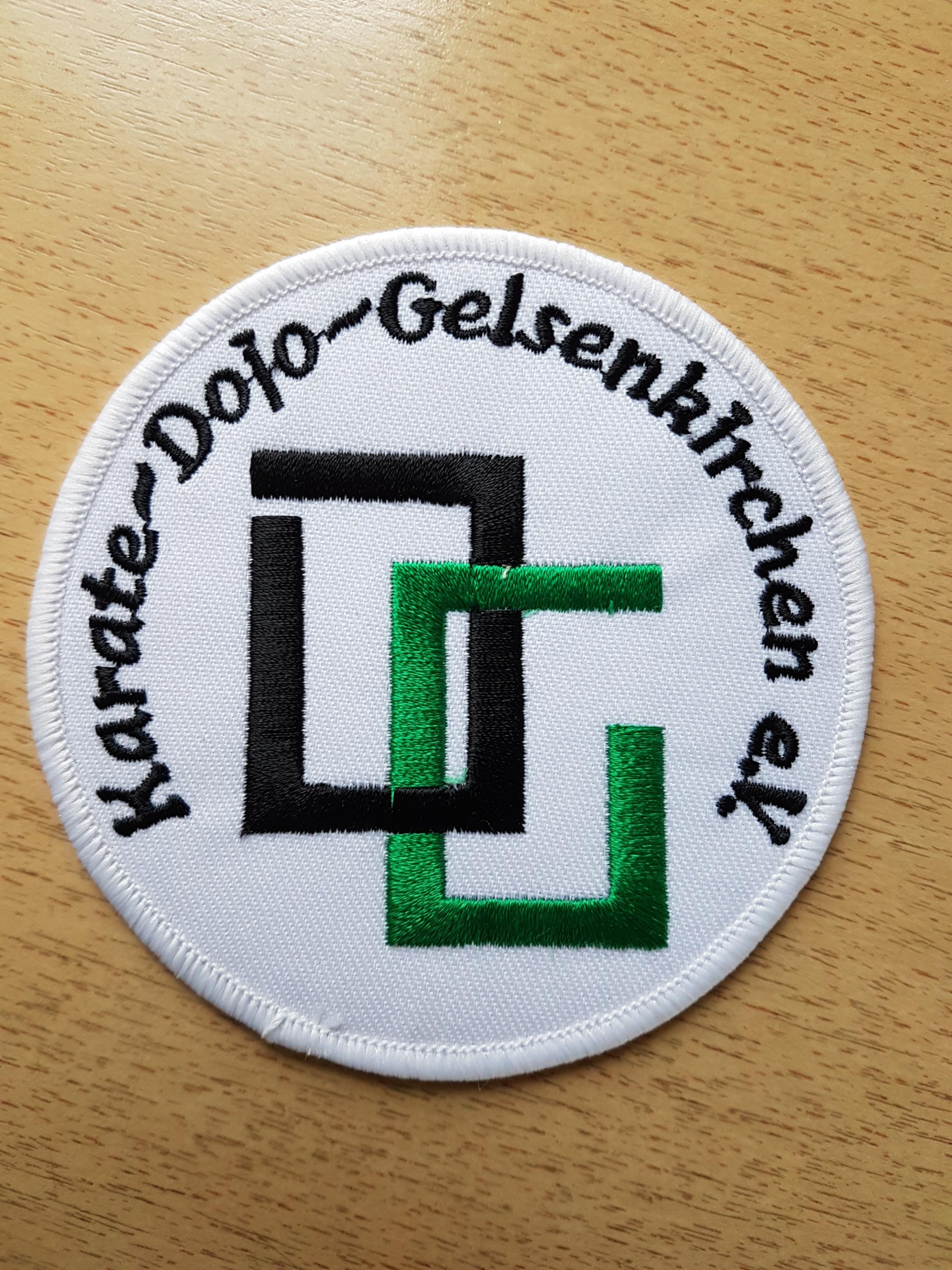
Frage zu angehängter Schrift
kann mir vielleicht jemand sagen, wie diese Schrift auf unserem Vereinsaufnäher heißt?
Das ist durch die Stickerei so verfremdet worden, dass es schwer sein könnte, die genaue Schrift zu finden. Eine ähnliche sollte es tun, um die gleiche Anmutung zu erreichen. Aber vielleicht solltet ihr euch die Frage stellen, ob eine andere Schrift für dieses Verfahren besser geeignet wäre. So ist das j in Dojo kaum als solches wahrnehmbar, und die geschwungenen Bindestriche bringen vielleicht noch mehr Unruhe in die ganze Sache.
Stickereien verwenden oft ihre eigenen Schriften, weil diese schon digitalisiert und für die Stickmaschine aufbereitet vorliegen. Ich würde zunächst die Stickerei fragen …
Kann mir denn vielleicht noch jemand sagen, wie eine ähnlich Schrift heißen würde.